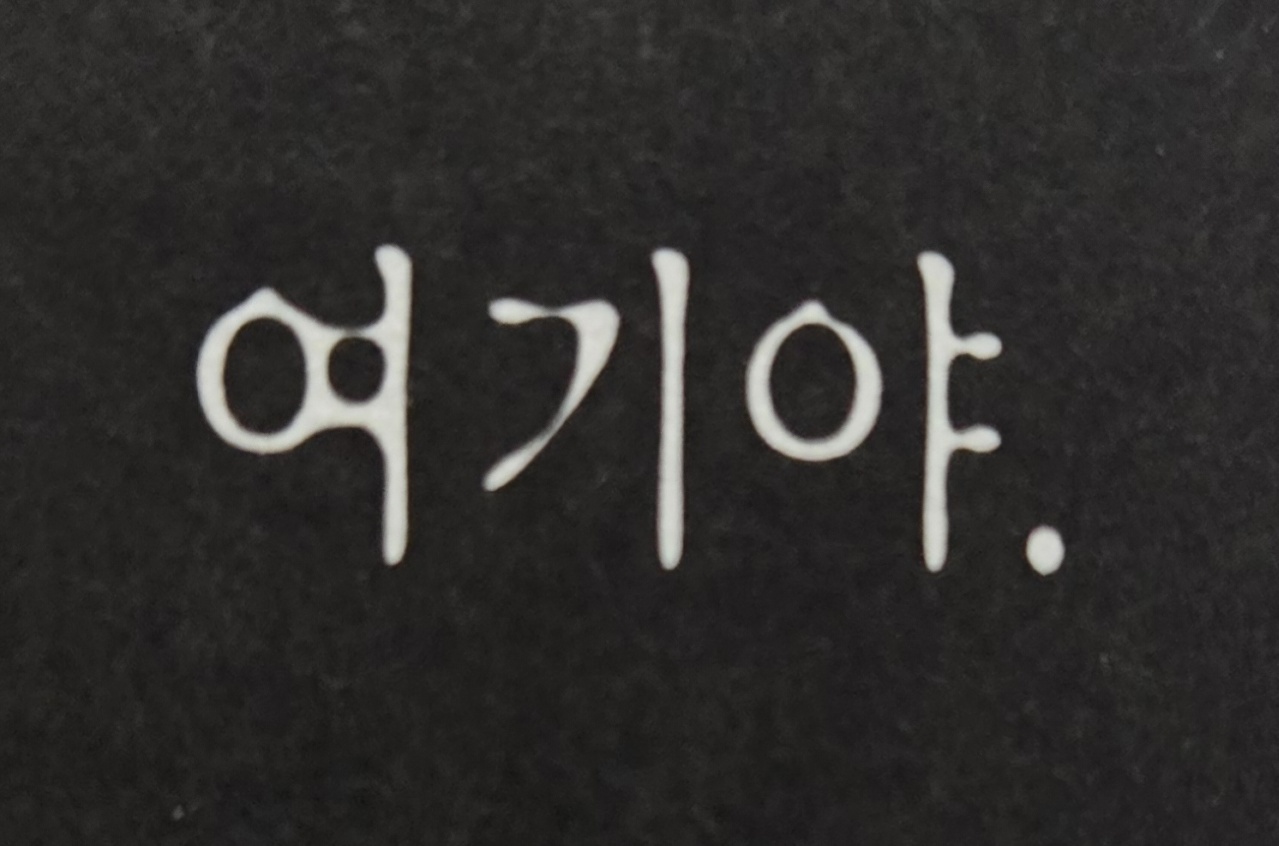
비슷한 폰트 찾아주세요 !!ㅠㅠㅠ
사진처럼 으스스하고 무서운 느낌이 드는 폰트를 찾고 있어요..!
1번째 사진은 210 미스테리 체에요! (제가 알기론 무료폰트인데 상업적 이용불가능한 폰트..)
2번째 사진은 폰트 알려주시면 감사할것 같습니다..!
Yoon 달팽이에 장평값을 줘서 가로폭을 좁게 하면 저렇게 나올 것 같네요 https://www.sandollcloud.com/font/20979/Yoon-Dalpaengi 폰코 골라담기 이용이 가능하면 더 저렴하게 이용할 수도 있을 듯(3개 이상 선택하고 가격 확인) https://font.co.kr/collection/pickFont